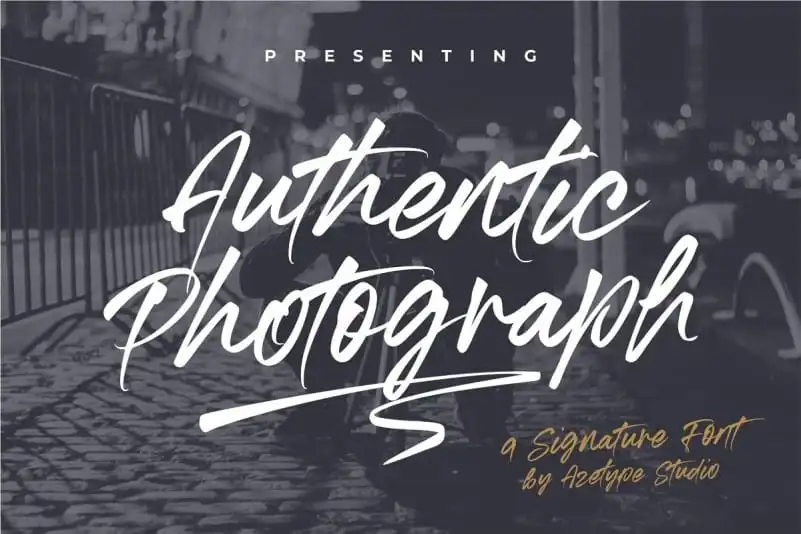
Authentic Photograph Signature Font – Download Grátis
Nossa nova adição à coleção de fontes é o “Authentic Photograph Signature Font”. Esta é uma fonte script com estilo moderno e influência natural das escritas manuscritas. Ela destaca-se por sua característica rica, onde cada detalhe meticulosamente produzido traz uma aparência tão próxima à escrita de palma livre quanto possível. Esta fonte foi cuidadosamente construída para reproduzir o jeito natural das escritas manuscritas, proporcionando um acabamento perfeito em cada letra. Ela é ideal para quem busca deixar seu documento com uma impressão autêntica e moderna que realmente faz a diferença. Existe a possibilidade de criar ligaturas como ‘tt’ onde o estilo fluido do ‘t’ se sobrepõe ao da letra original, dando um toque único e natural ao resultado final. Experimente essa funcionalidade imediatamente em seu próximo trabalho!